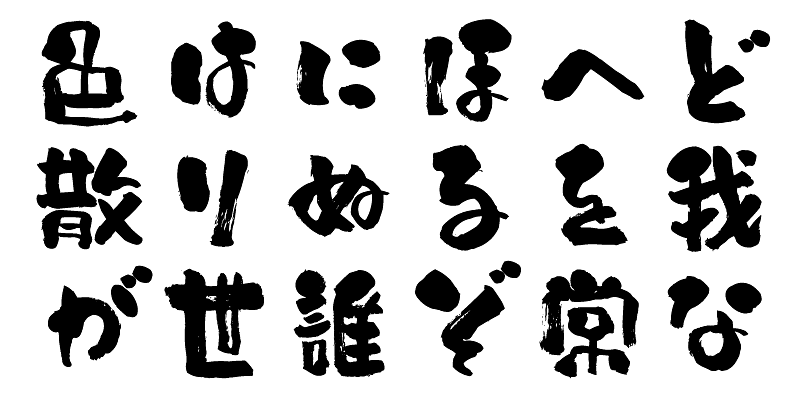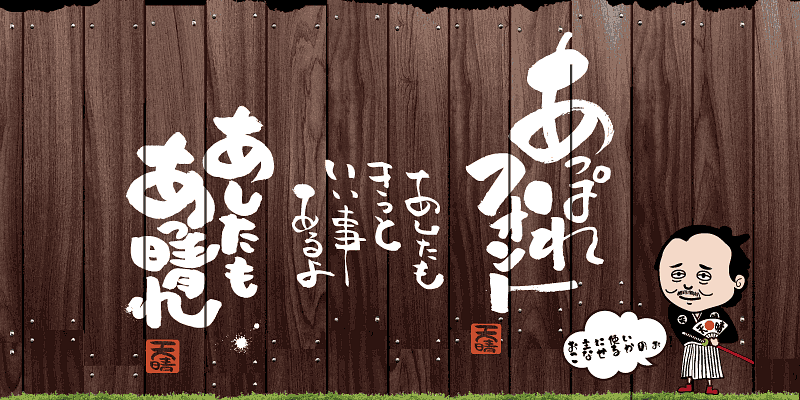
このフォントには、新聞社、出版社、国語研究所等の使用頻度表から選んだ上位 1,000 個の漢字に加え、206 個の両仮名および約物が含まれています。
このフォントシリーズは、2002 年に発売されたペン習字をベースにした手書きの日本語オリジナル書体です。温かみのある表情で、読む人の目をデザインの重要なポイントに引きつけます。